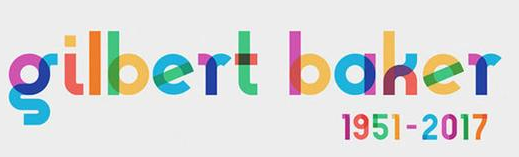
Gilbert是全球首款彩虹字體,絢麗的顏色讓你的文字更顯得生動(dòng)活動(dòng),作者寓意“驕傲的打字”,無(wú)論是收藏還是使用,這款字體都值得被擁有,綠色資源網(wǎng)誠(chéng)意推薦!
創(chuàng)作這款字體的原因是彩虹旗的創(chuàng)造者 Gilbert Baker 在 3 月 31 日于家中逝世,為了紀(jì)念 Gilbert 及其對(duì) LGBTQ 群體的貢獻(xiàn),創(chuàng)作團(tuán)隊(duì)將彩虹旗的設(shè)計(jì)語(yǔ)言轉(zhuǎn)換成字體。字體的顏色都來(lái)自彩虹旗,在筆畫(huà)相疊處半透明的設(shè)計(jì)組合成新的色彩。